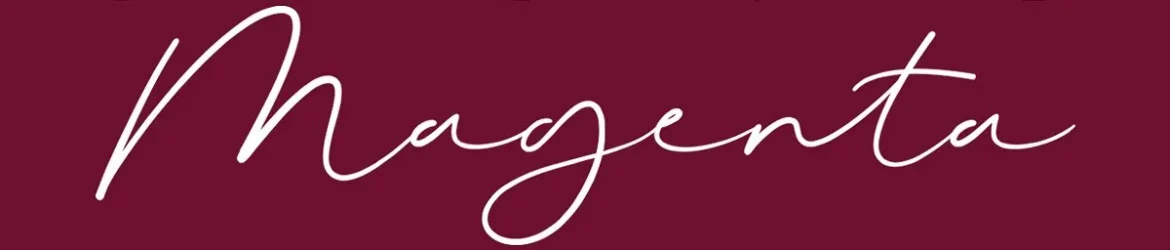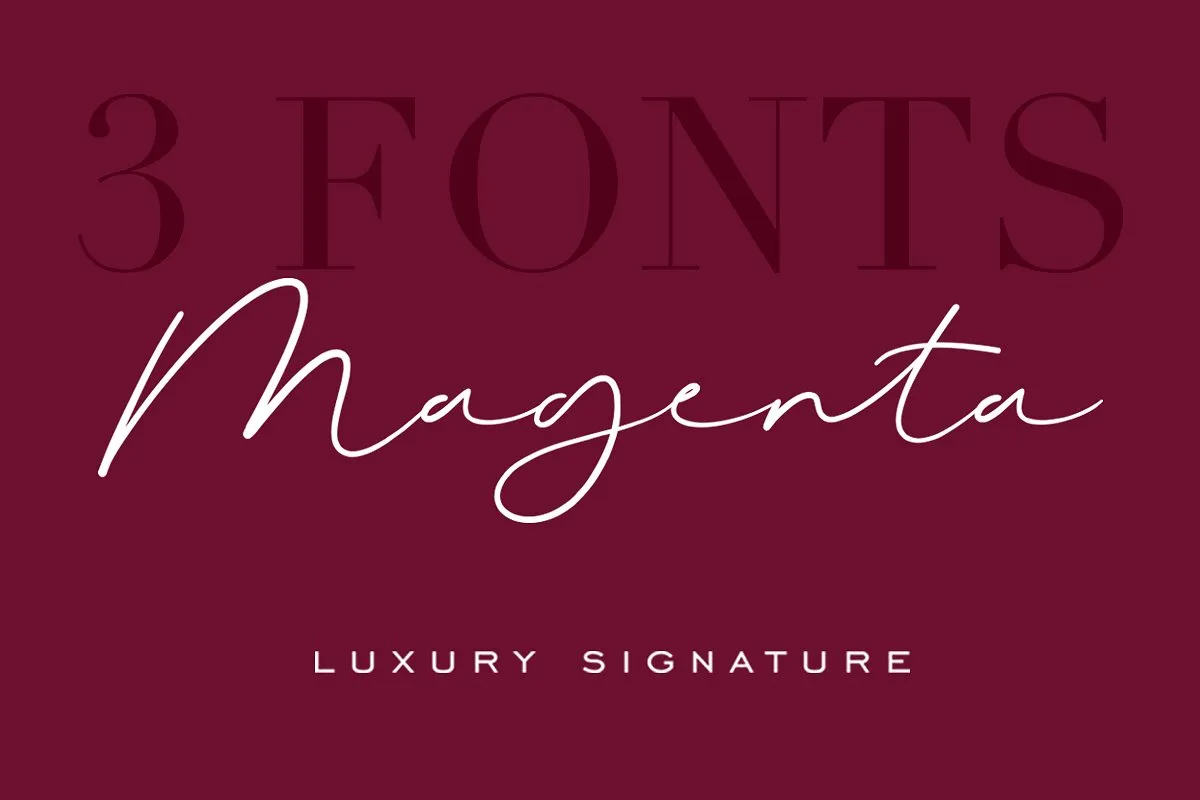
Magenta Signature Font – Fonte Grátis
Magenta Signature Font
A Magenta Signature Font é uma opção perfeita para profissionais que desejam adicionar elegância sofisticada a seus projetos sem perder o tom descontraído e desconformista. Inspirada no design de letra chique e delicado do designer 178-MC, esta fonte script incorpora características modernas, adequadas para apresentar produtos e serviços de alta qualidade. As linhas finas e os traços suaves da Magenta Signature Font criam um estilo elegante enquanto a personalização livre nos caracteres permite uma letra única que se assemelha a uma assinatura. É perfeitamente adaptável aos profissionais de design que desejam adicionar um toque único e luxuoso a seus projetos digitais, seja em aplicativos de design ou sites web. A Magenta Signature Font oferece uma combinação perfeita de elegância e descontração, adequada para designers que querem se destacar no mercado digital atual.